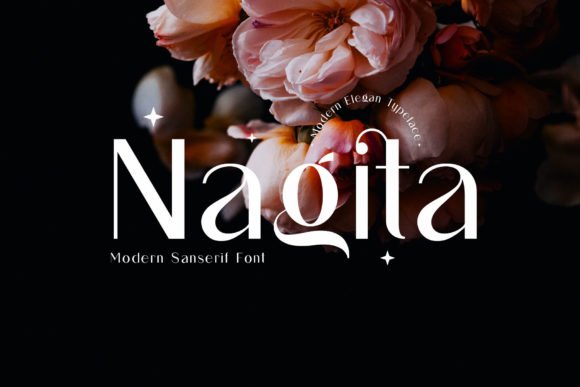
Nagita - это современный и элегантный шрифт без засечек.
Он имеет чистую, тонкую и гладкую вибрацию и станет хитом для любого дизайна, в который вы захотите его добавить.